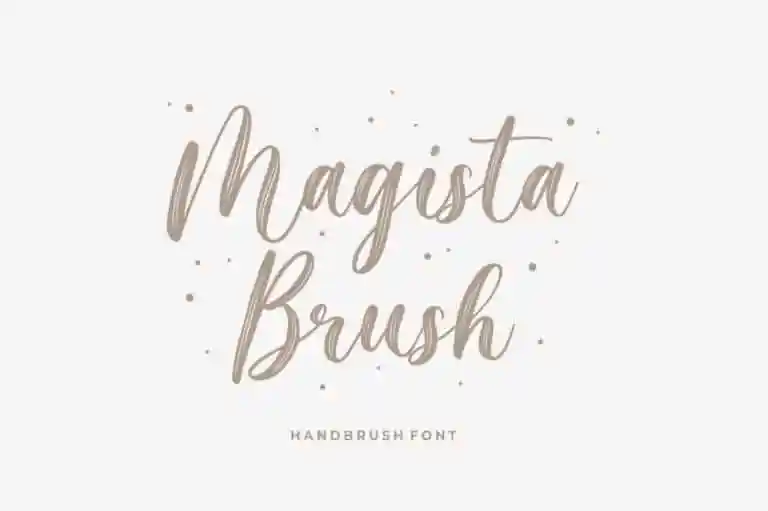
A Magista Brush Font é uma tipografia natural inspirada no uso das mãos para escrever, com sua aparência moderna e sofisticada. Este tipo de letra foi projetado pela Sronstudio e compartilhado como parte do catálogo da 99designs. Perfeita para um vasto range de aplicações, a Magista Brush é ideal para criação de marca, convites, embalagens de material de escrita, design para casamentos, postagem no Facebook ou Instagram, publicidade, embalagens de produtos, etiquetas, fotografias e até mesmo marcas especiais em eventos. Com sua graça natural e estilo moderno, a Magista Brush é uma escolha perfeita para qualquer projeto que busque um toque elegante e único.